如今设计创作的需求越来越多元,一款适配的字体能让作品的质感和表达力大幅提升,而找字体时的版权顾虑、资源杂乱问题却常让人头疼。我一直想为大家整理些实用又靠谱的下载在线免费字体的渠道,本文就给大家推荐 4 款优质的在线免费字体网站,满足各类设计的字体需求。
字由网
聊到在线免费字体网站,我第一个要推的就是字由网。字由网的核心就是在线免费字体管够、好用还合规。平台上大概有5000多款在线字体,其中1000多款都是厂商公开授权的免费商用款,像我们平时常用的思源黑体、站酷系列、阿里妈妈普惠体,还有抖音美好体,这里全都能找到。每款在线字体下面,都会清清楚楚标着版权声明和使用范围,有源可查,不管是自己做个小海报、发个推文,还是商用项目(比如客户的海报设计、品牌周边),用着都特别安心。
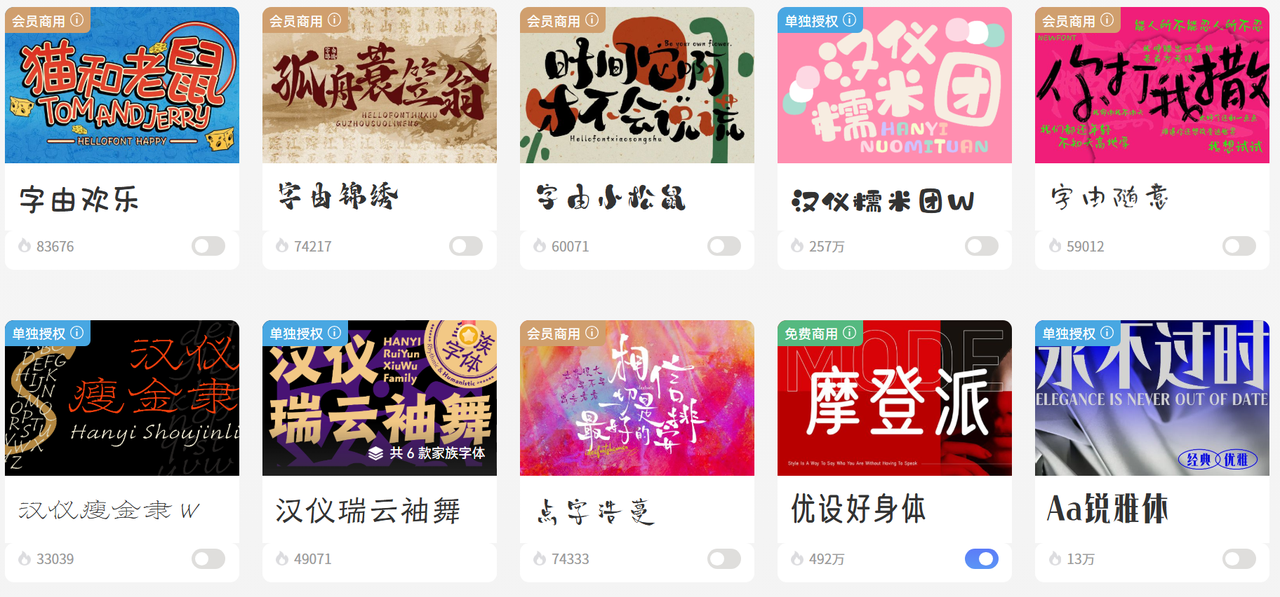
还有个特别省心的设计,就是在线免费字体都是“即选即用”,不用像以前那样,下载完字体还要繁琐安装,占电脑内存不说,切换起来还麻烦。
除此之外,它还自带AI识字、字体特效等实用功能,遇到未知字体,上传图片就能秒识别;想做特色标题字,一键就能生成金属质感、手绘、3D立体等多种风格,极大降低了设计门槛。
而且它的在线免费字体的分类也特别清晰,书法体、手写体、创意体、无衬线体,想找什么风格,点对应分类就能找到,也能按热门程度、最新上线来筛,输入字体名字,一秒就能搜到,不用翻来翻去浪费时间。
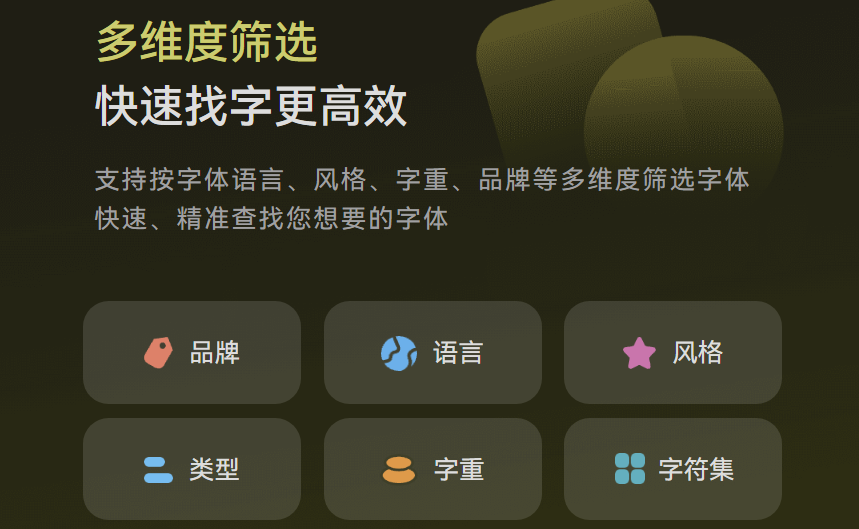
猫啃网
猫啃网是国内少数专注于中文免费商用字体的平台,也是我找手写体、复古风字体的首选网站,亲测资源优质、更新频率极高,经常能挖到刚发布的小众创意字体。目前平台收录了近千款优质在线免费字体,涵盖楷书、行书、草书、手写体、复古体、卡通体等多种风格,尤其是手写体和复古风字体,款式比其他网站更丰富,像“猫啃硬笔楷书”“站酷快乐体”等特色字体,能瞬间提升作品的差异化。
Google Fonts
如果大家有英文字体需求,那Google Fonts绝对是绕不开的宝藏平台,也是我平常会使用到的英文在线免费字体网站之一。平台收录了1000+款高质量英文字体,涵盖无衬线体、衬线体、手写体等多种风格,适配各类设计场景,字体清晰度高。虽然以英文字体为主,但也包含了思源黑体等优质中文字体,满足中英文混排的需求,兼顾实用性与专业性。
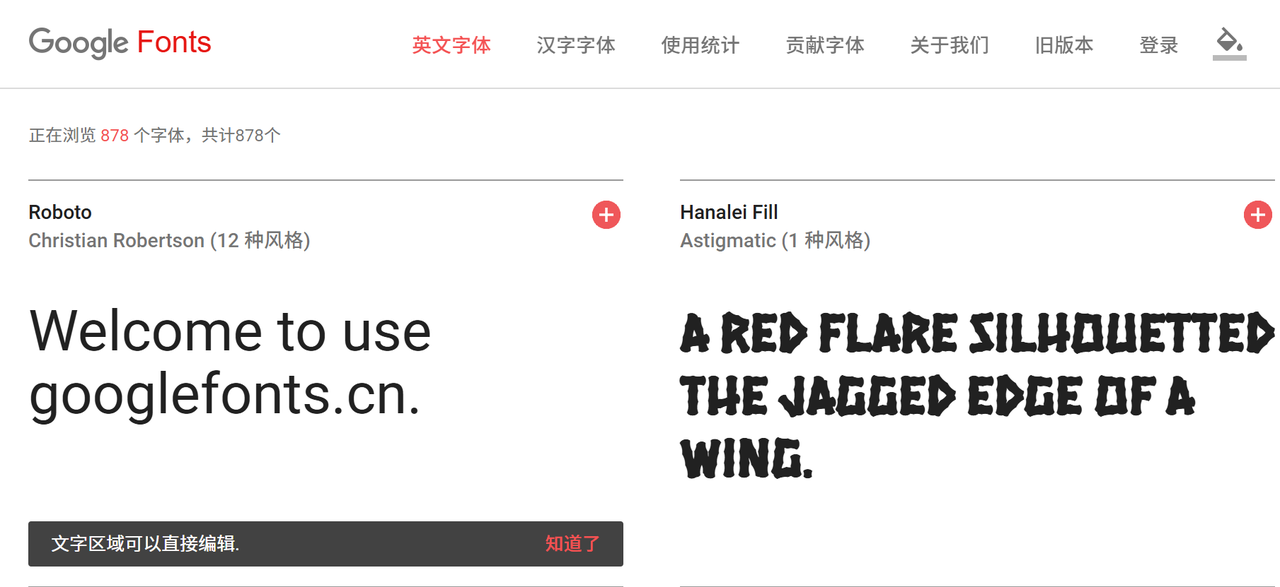
优设字体导航
最后一款推荐的是优设字体导航,优设字体导航更像是一个“免费字体导航地图”,它本身不直接提供在线免费字体下载,而是整合了国内外优质的在线免费商用字体资源,严格筛选出经过官方授权、真正免费商用的字体。对于新手设计师来说,既是下载工具,也是学习助手,实用性拉满。